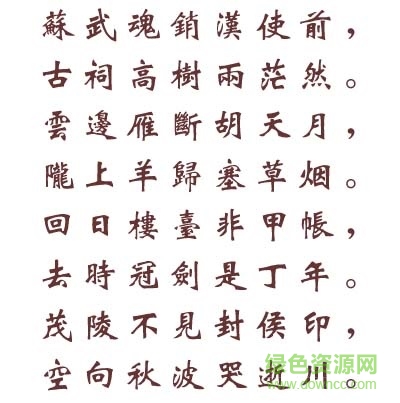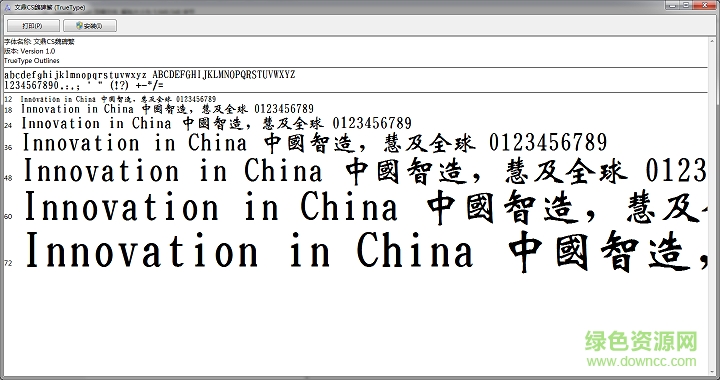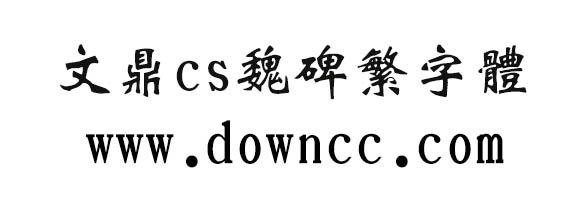
文鼎cs魏碑繁字體
文鼎cs魏碑繁體是文鼎字體庫(kù)中的一款魏碑繁體字體,筆畫(huà)略粗,撇拉都帶有拉長(zhǎng)效果。趕快到綠色資源網(wǎng)下載體驗(yàn)吧!
文鼎cs魏碑繁體介紹
文鼎cs魏碑繁體有點(diǎn)想楷體端端正正,在個(gè)別的漢字中又會(huì)帶有繁體字的文化特色,是現(xiàn)在非常使用的字體之一